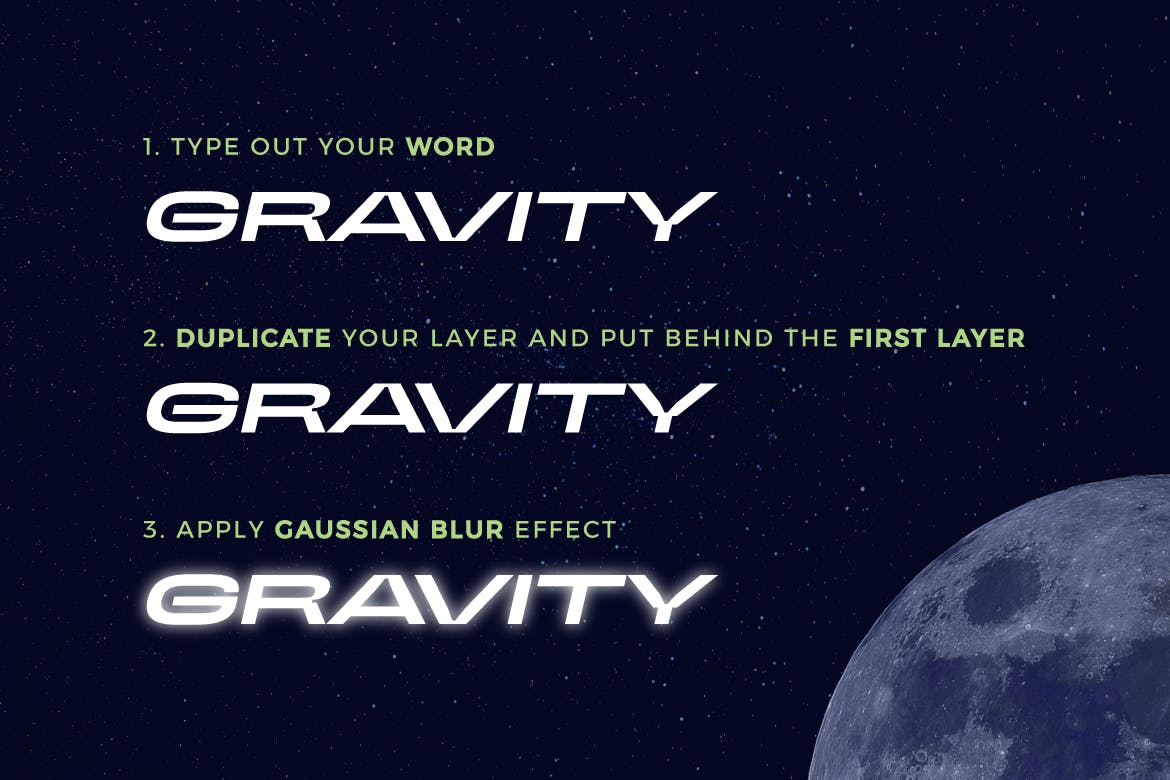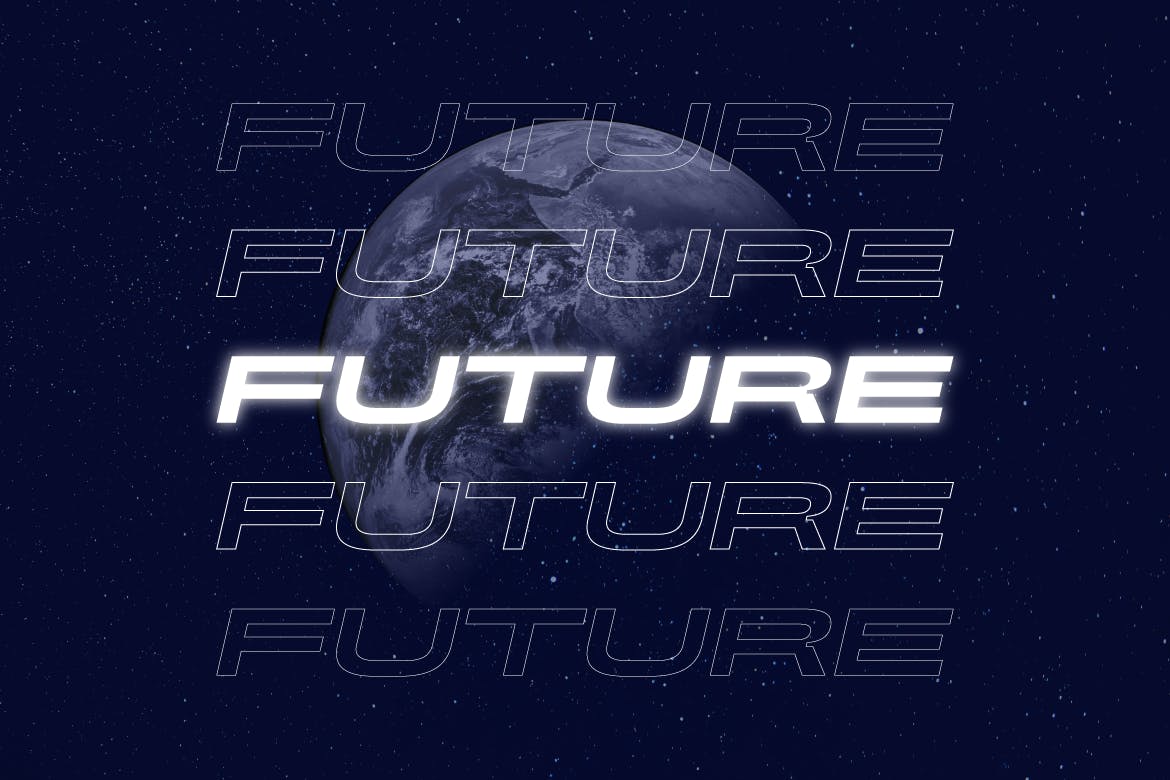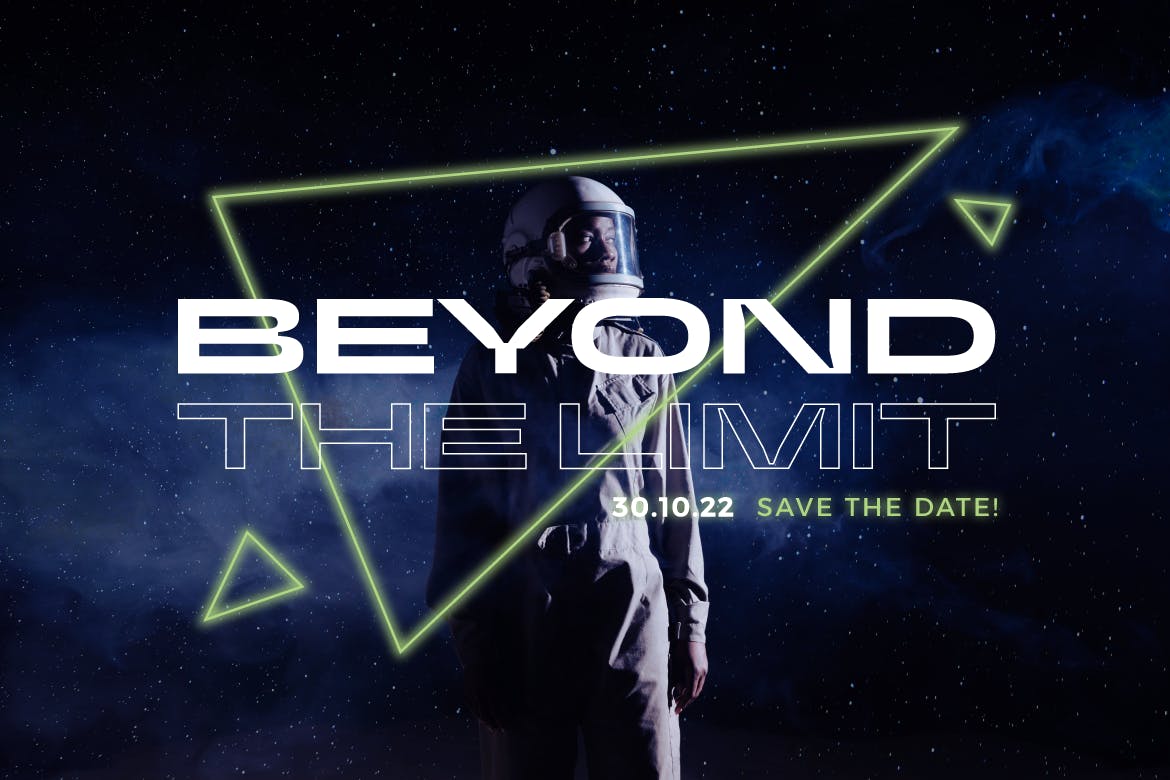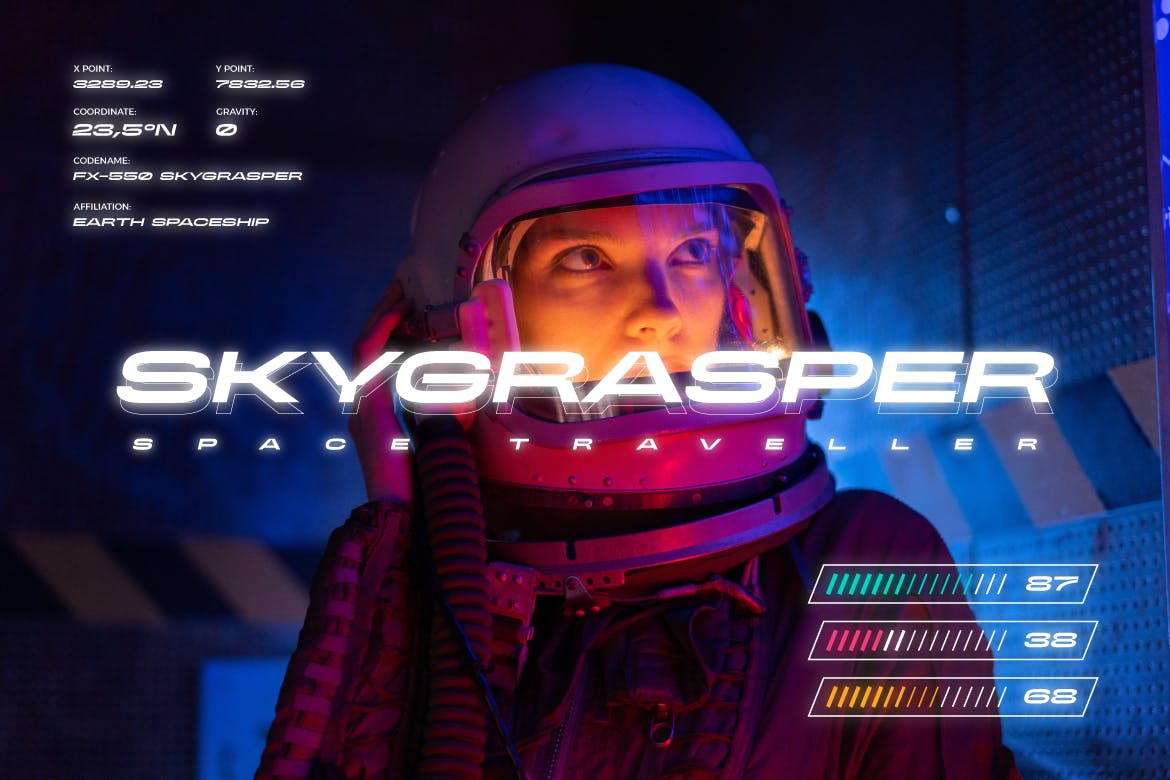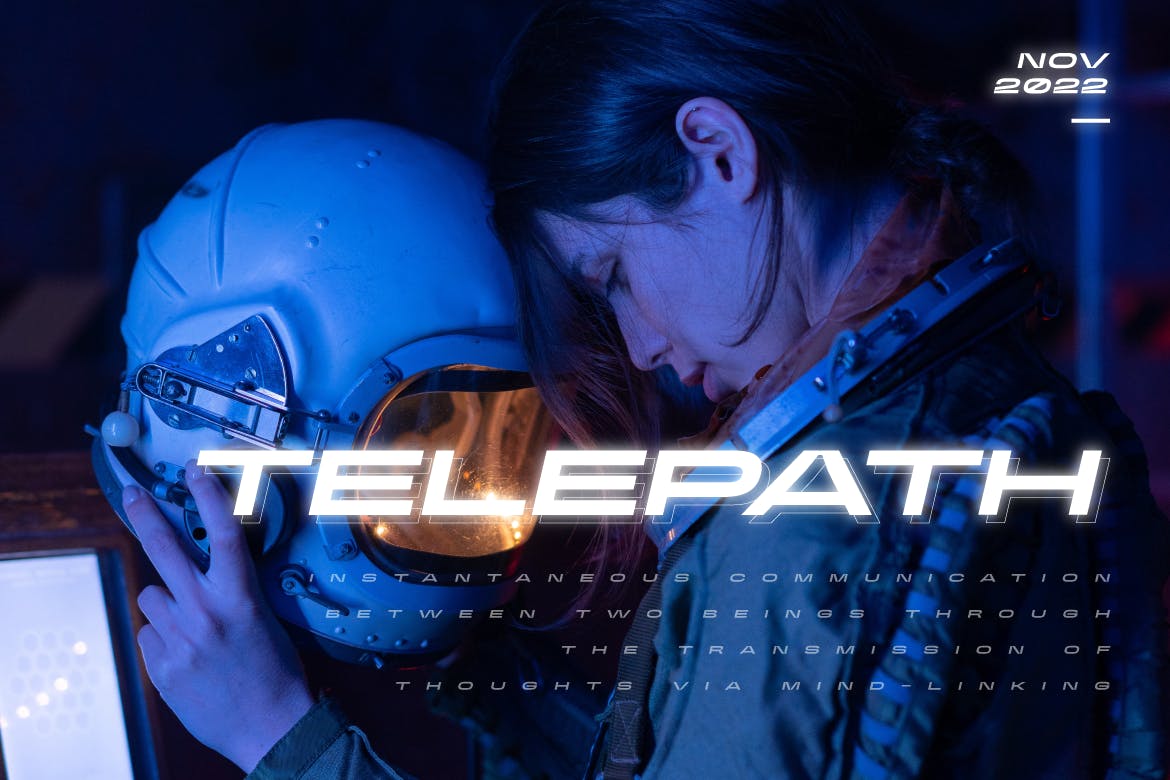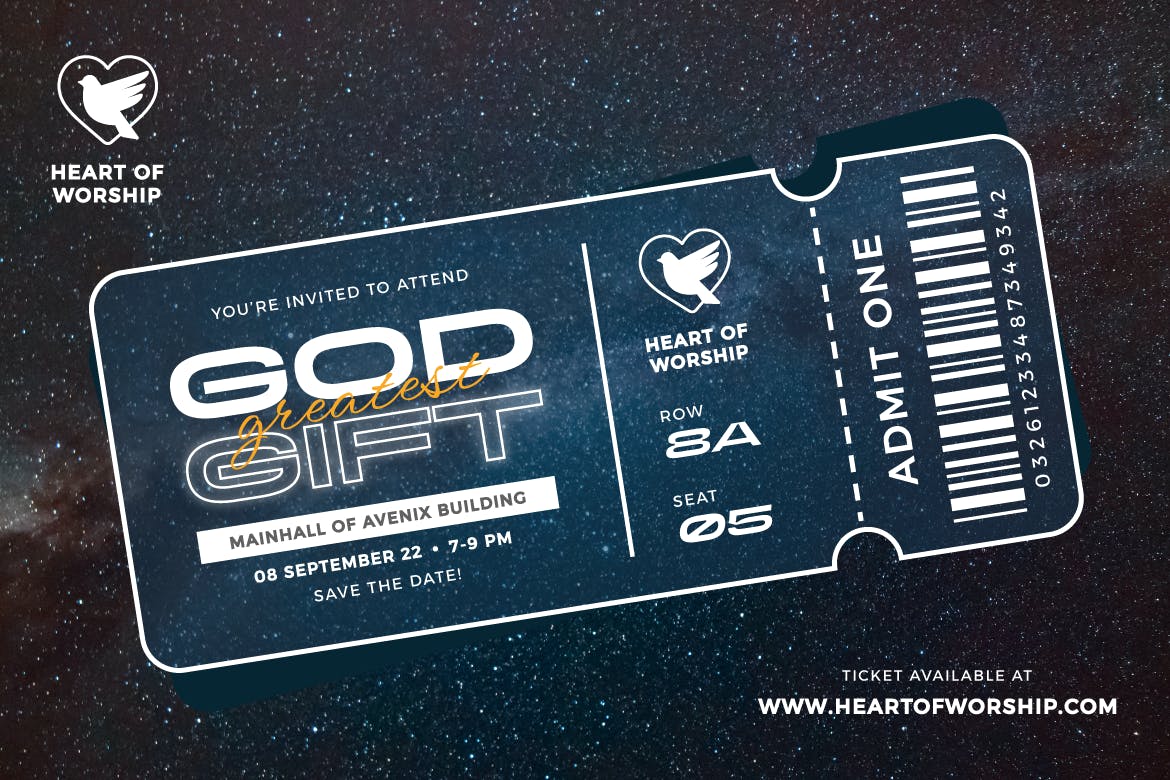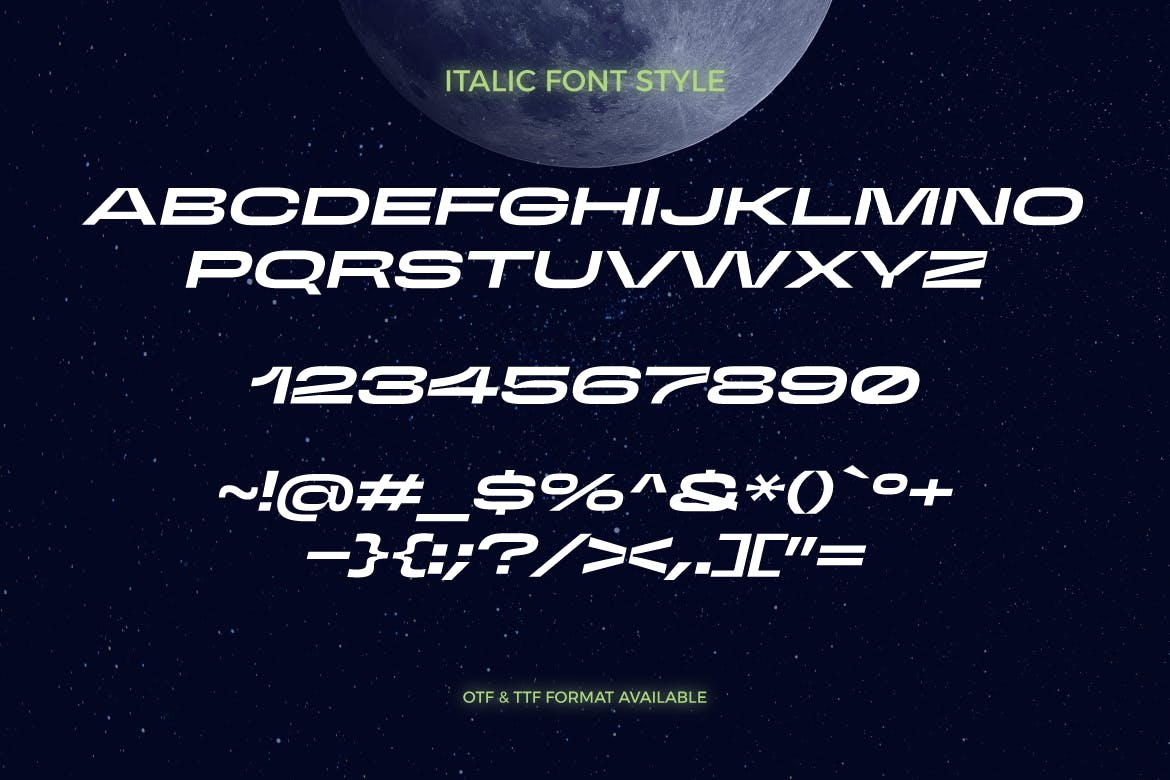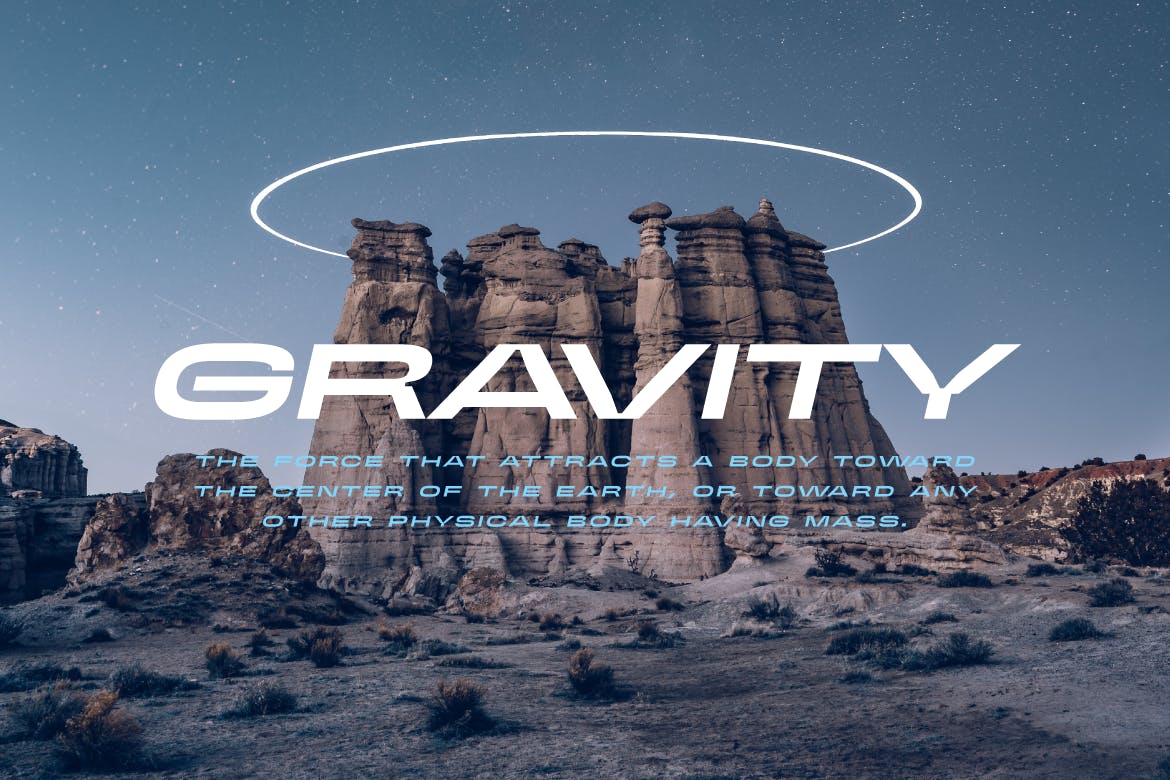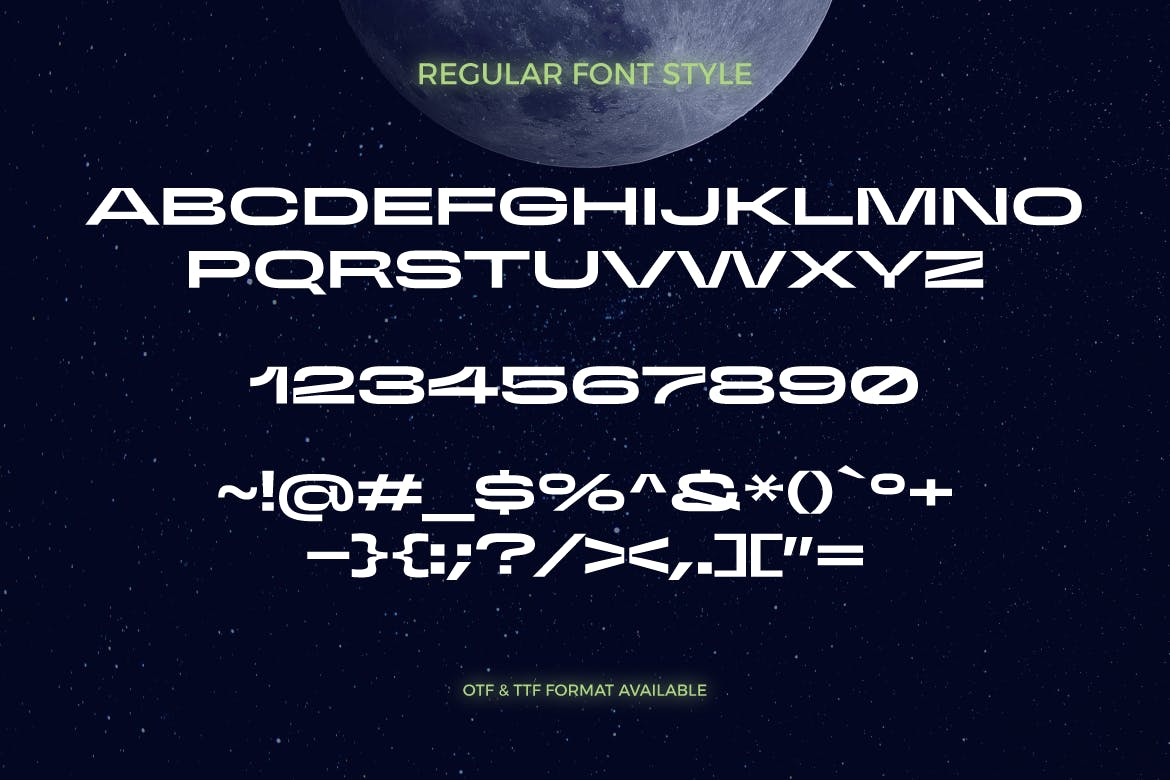
فونت Avenix، یک فونت مدرن و تمیز از نوع سنس سریف با حس و حال آیندهنگر است. این فونت دارای دو سبک معمولی و ایتالیک میباشد. Avenix برای طراحی پوسترها، فیلمها، بازیها، عناوین، برندینگ و بسیاری موارد دیگر انتخابی عالی است.